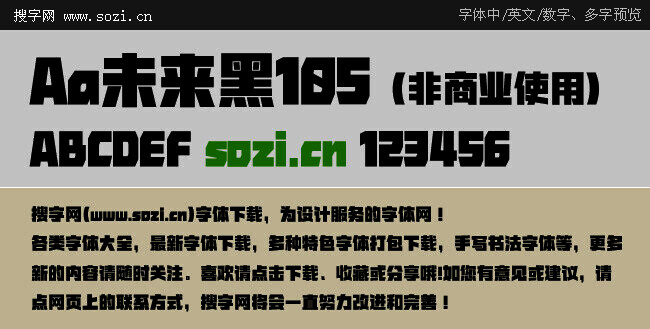
Aa未來(lái)黑105
搜字網(wǎng)給大家提供一款A(yù)a未來(lái)黑105(非商業(yè)使用)中文字體下載,該字體是一款藝術(shù)黑體,字體筆畫粗細(xì)一致,運(yùn)筆自然流暢,結(jié)構(gòu)清晰易識(shí)讀,以簡(jiǎn)單斜切的筆畫和方正飽滿的結(jié)構(gòu),來(lái)體現(xiàn)機(jī)械冷靜卻充滿力量的科技感,適合書裝設(shè)計(jì)、包裝、海報(bào)設(shè)計(jì)等應(yīng)用(此字體為個(gè)人非商用版,商用可以聯(lián)系QQ:1006760504)。